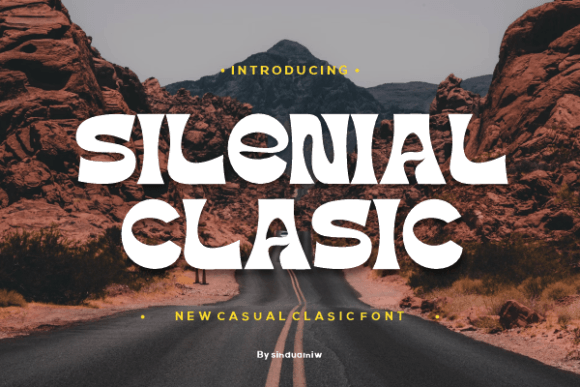
Silenial Clasic
適切なデザイン要素を見つけるのは難しい場合がありますが、Silenial Clasicは作品を即座に引き立てる優れたコレクションを提供します。
POD(オンデマンド印刷)製品、結婚式の招待状、またはソーシャルメディアのグラフィックを作成している場合でも、Silenial Clasicは理想的です。